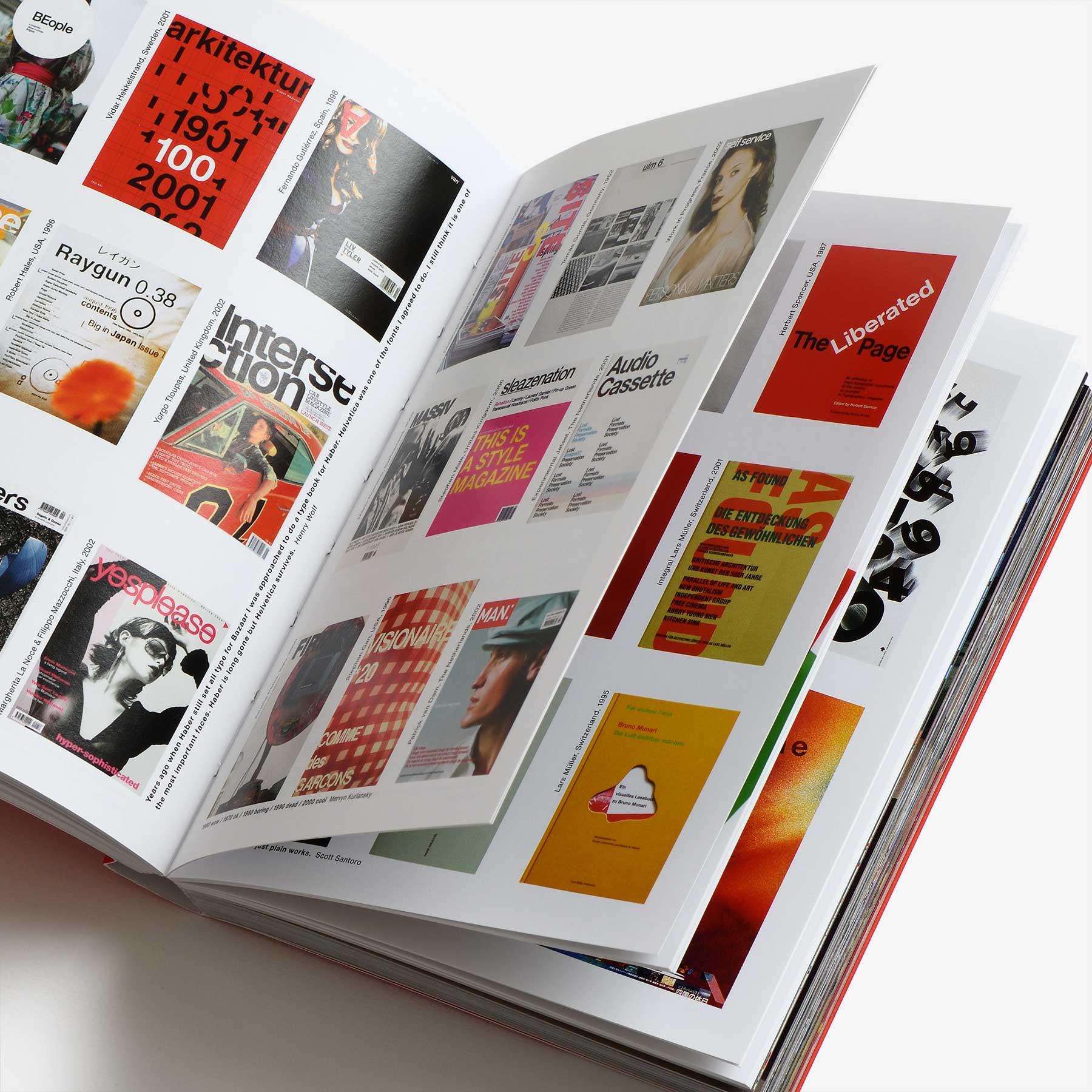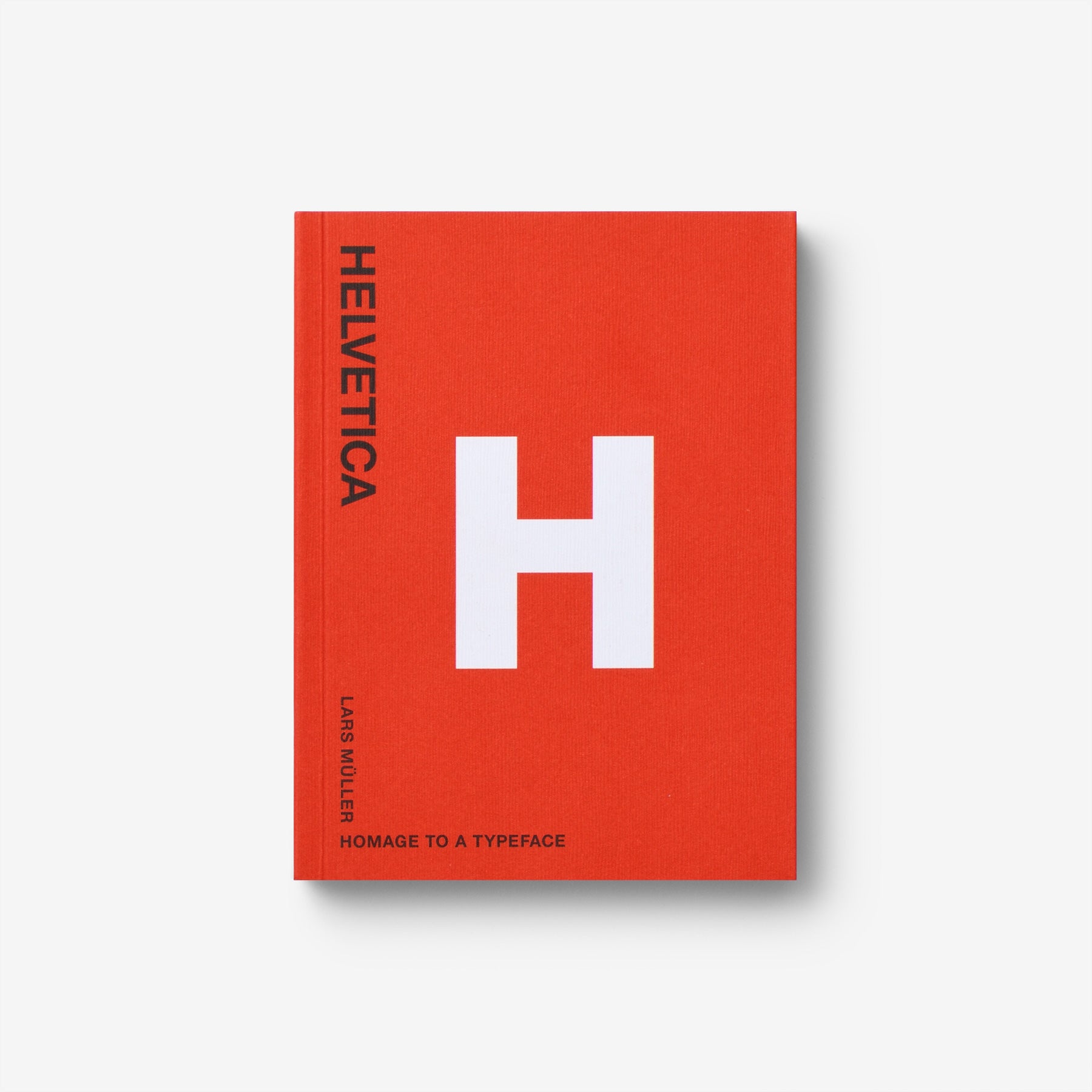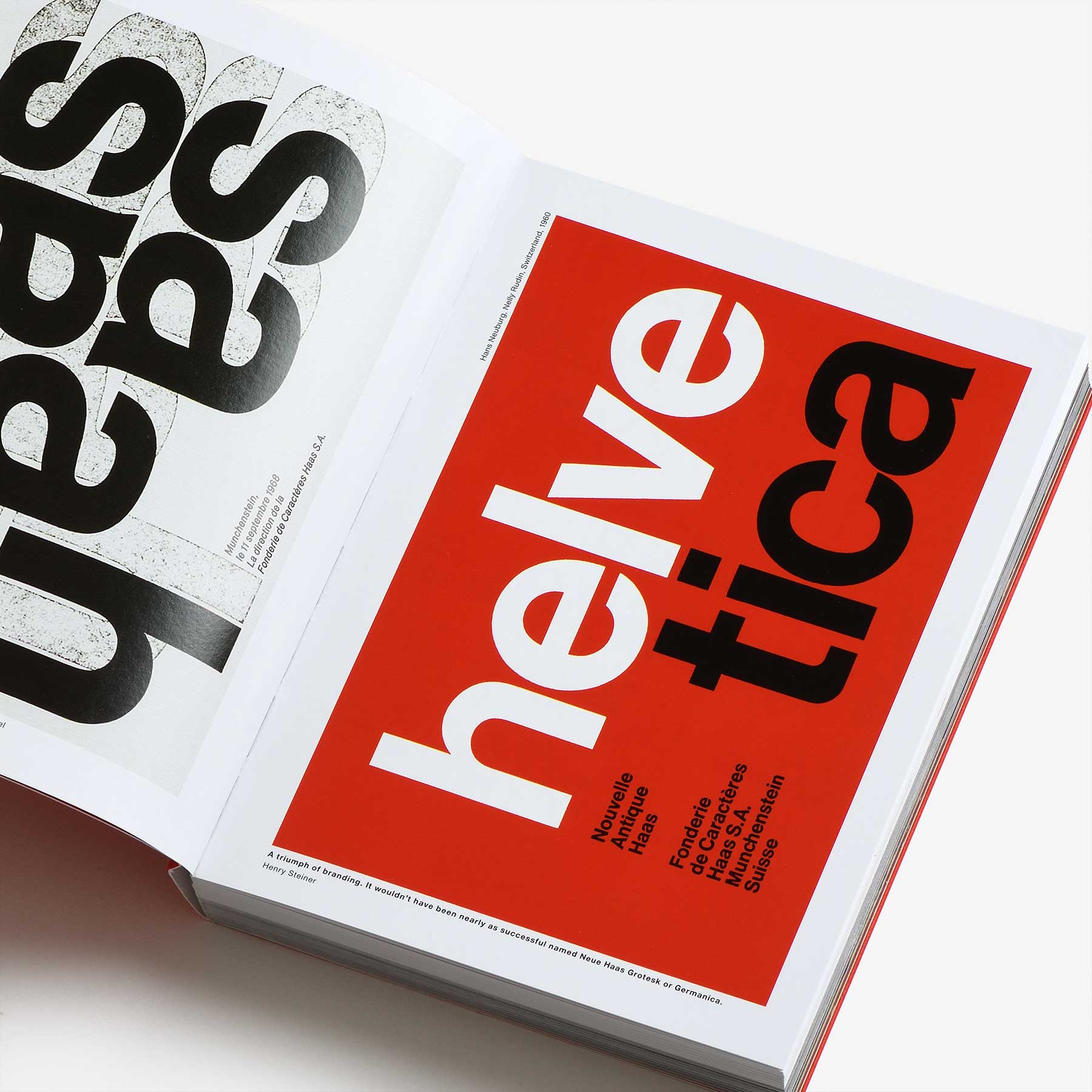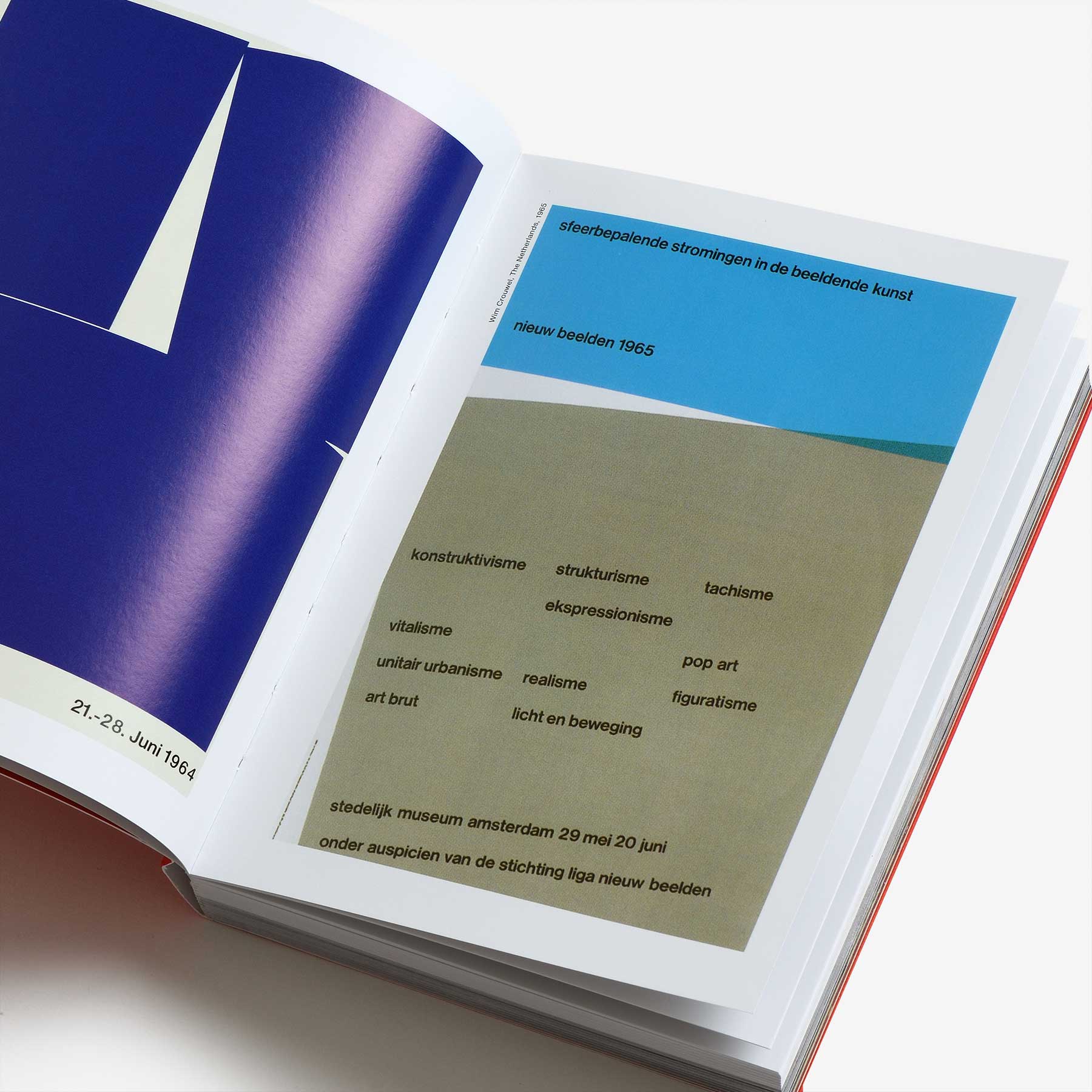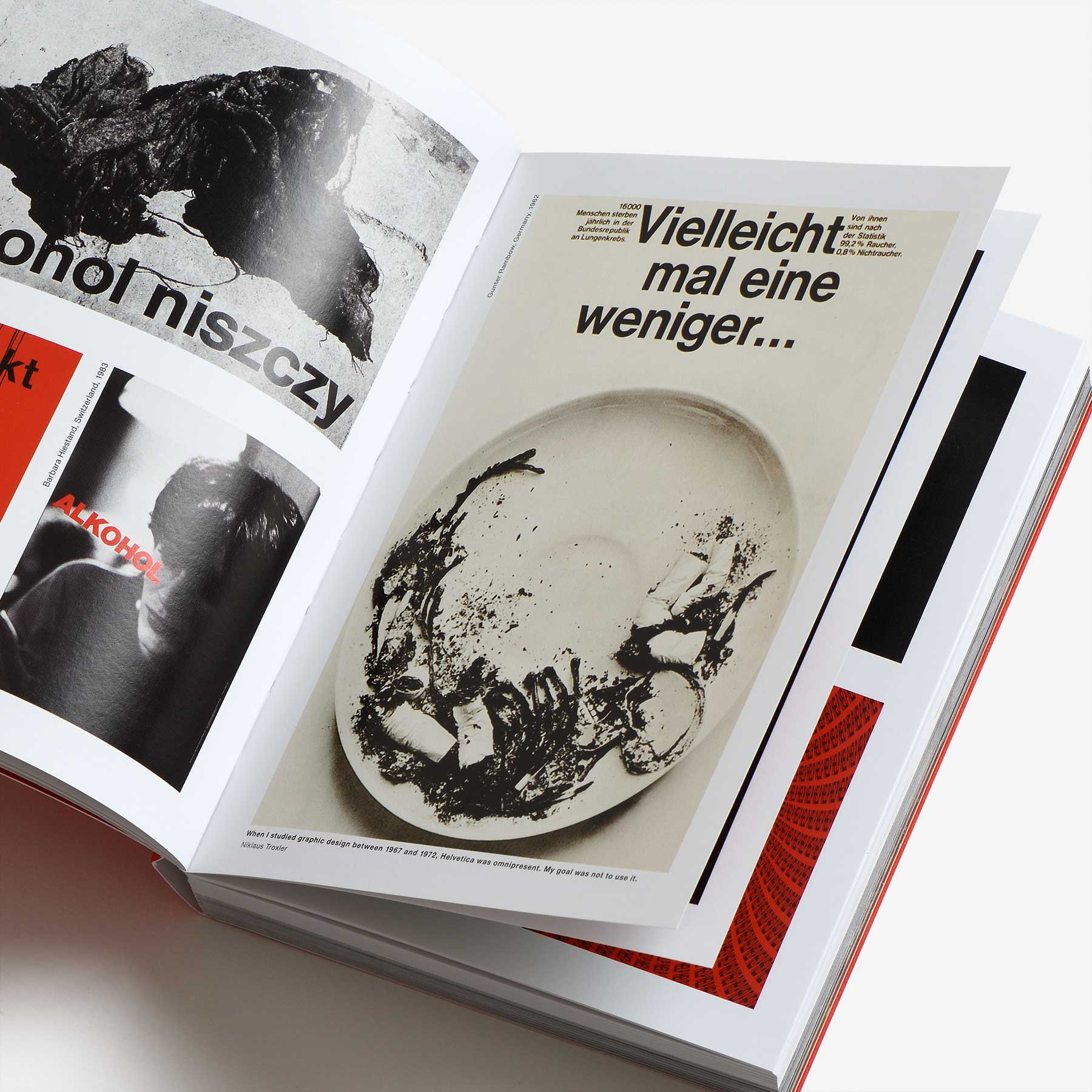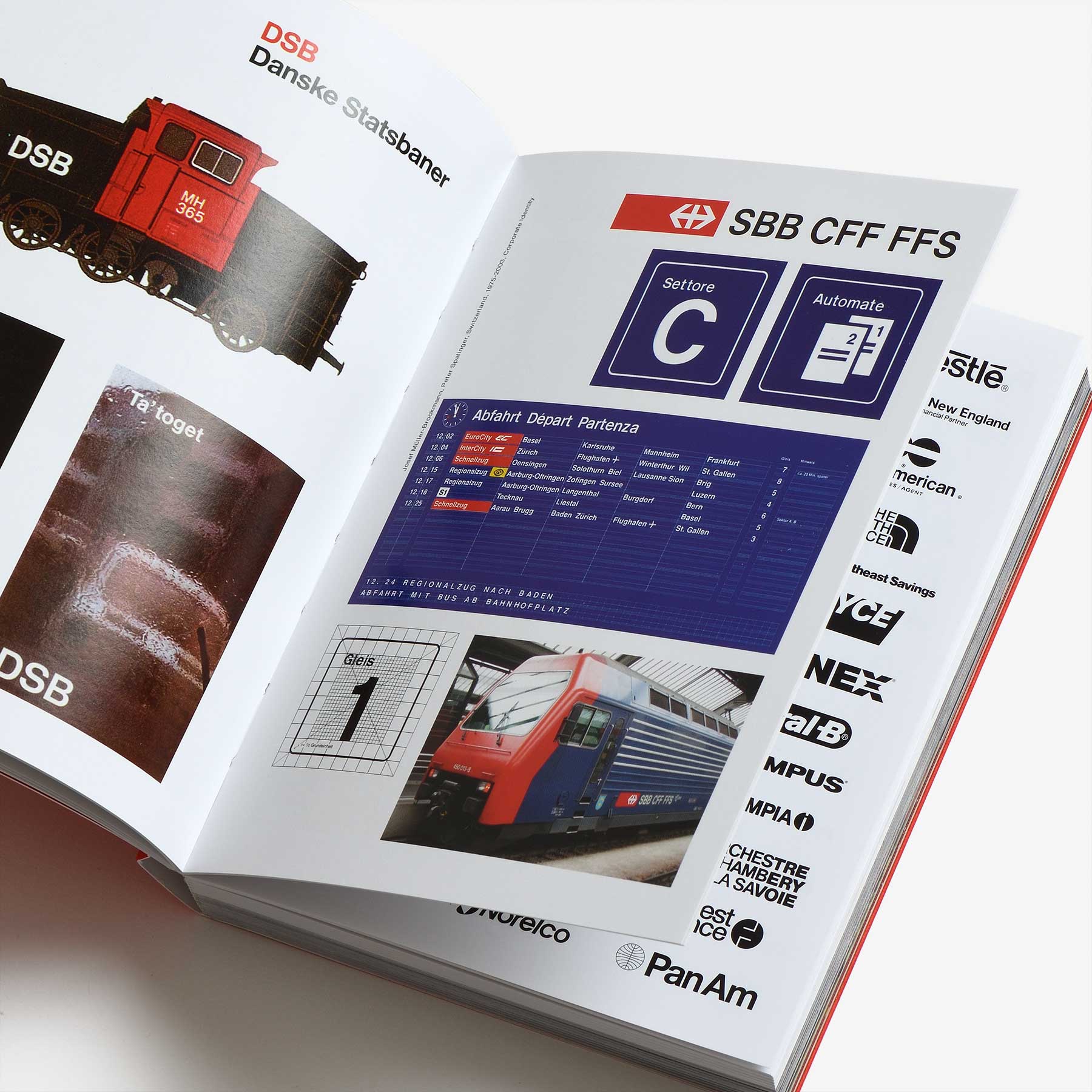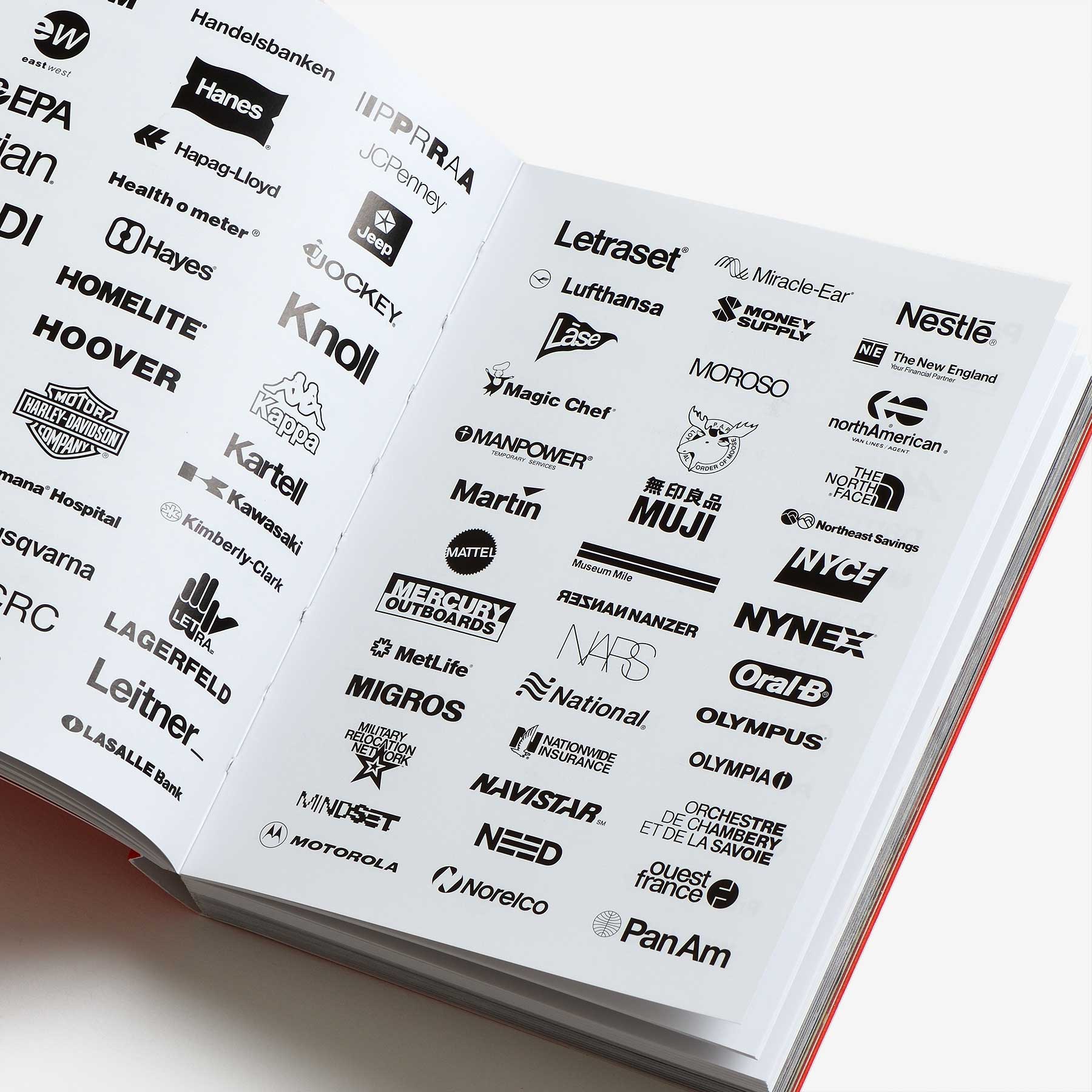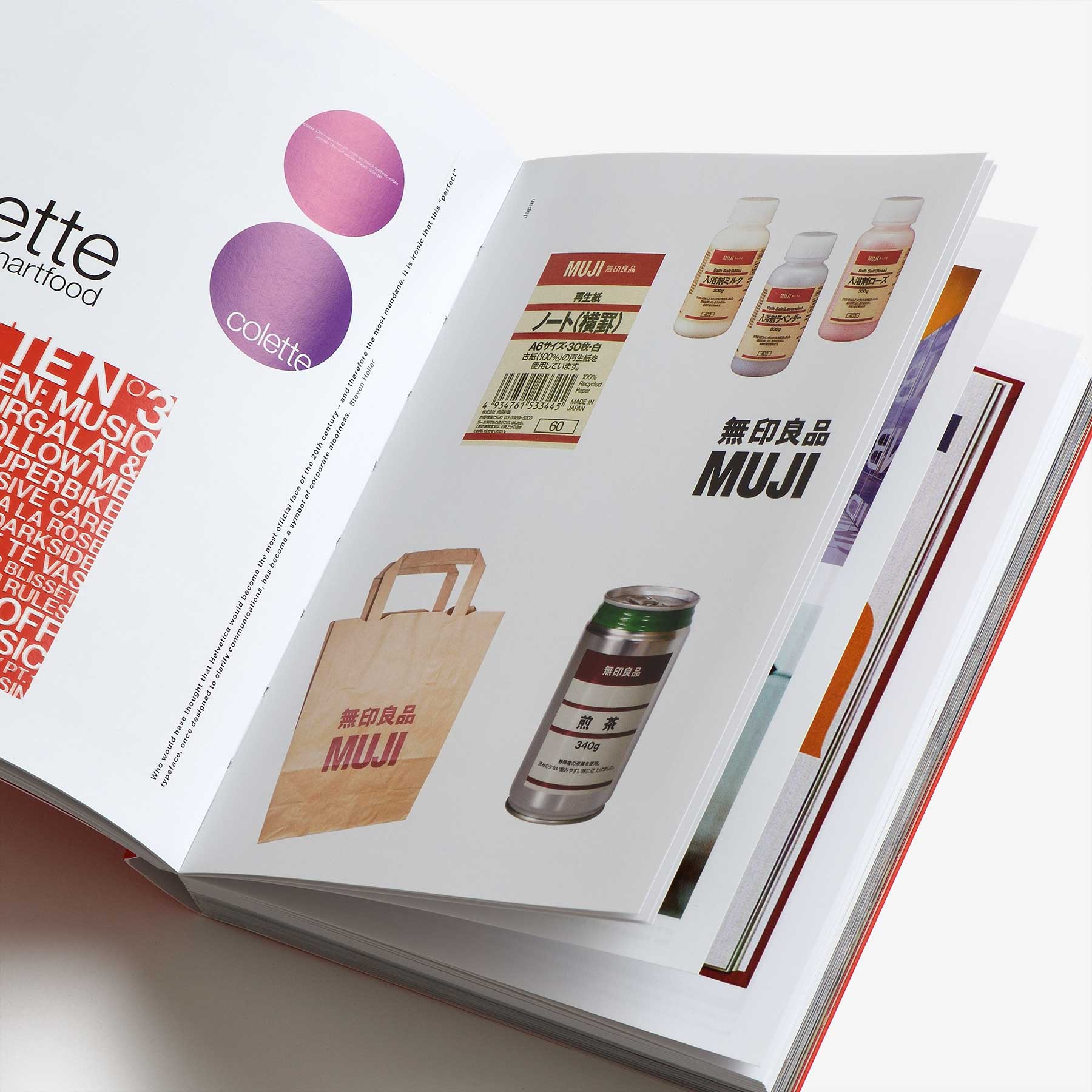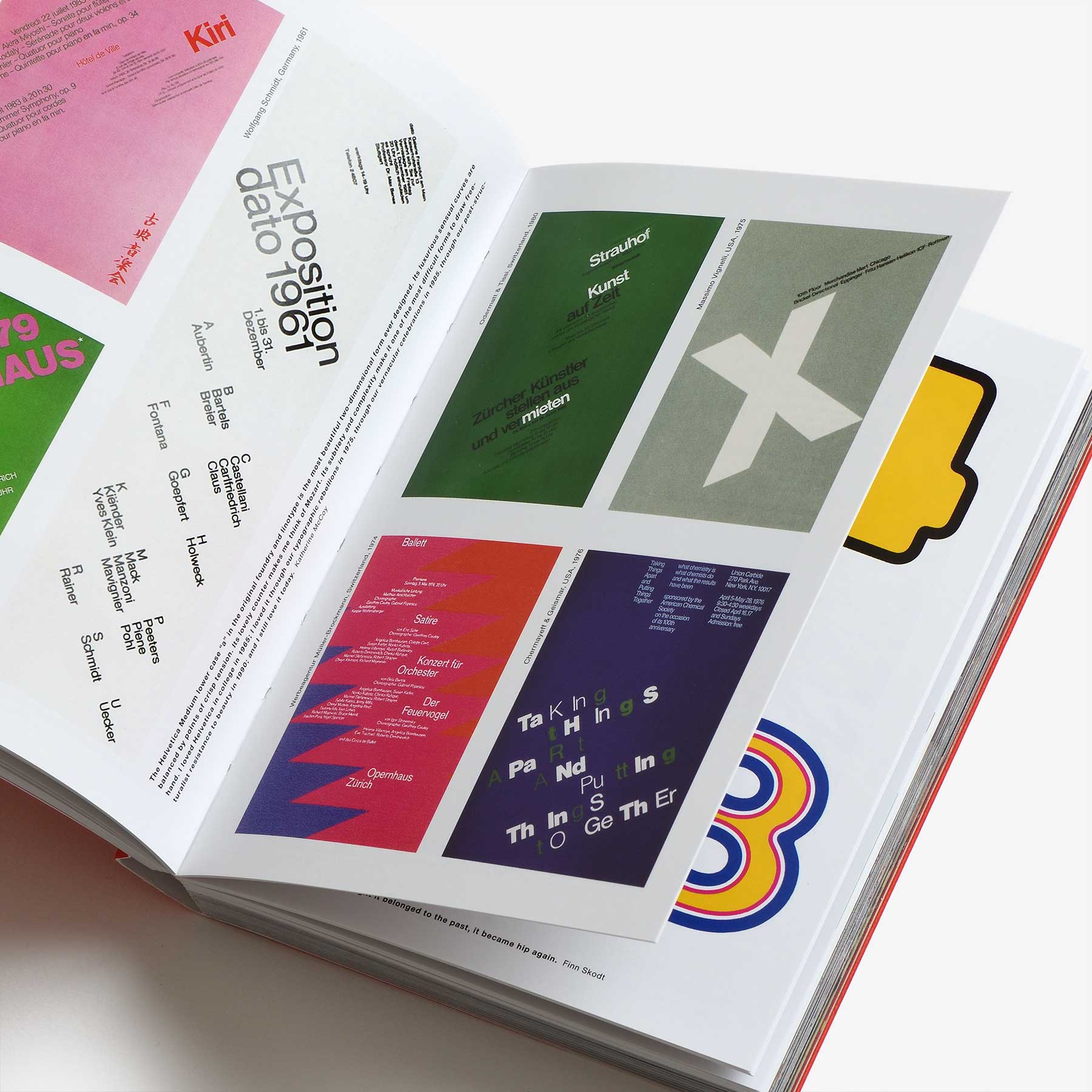
Helvetica: Homage to a Typeface
1957年、スイスのタイポグラファー、マックス・ミーディンガー(Max Miedinger)が書体「ハースグロテスク(Haas Grotesk)」を考案しました。 1960年以降、ヘルベチカ(Helvetica)と改名されたこの書体は、世界で最も使用されている書体の1つになりました。本書では、ヘルベチカに敬意を表し世界中からヘルベチカが使われた作品が集められています。